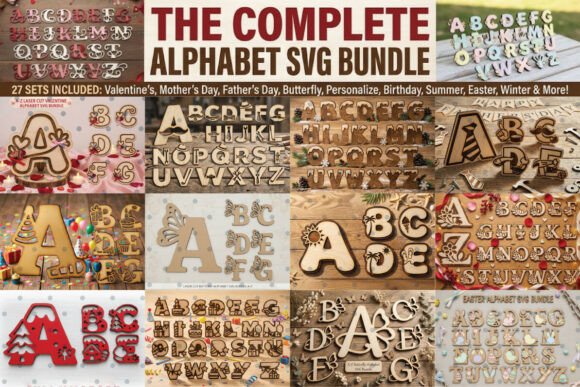
The Complete Alphabet SVG Bundle
Ulasan Lengkap: The Complete Alphabet SVG Bundle – Solusi Final untuk Desain Kreatif Anda
Ingin memperluas katalog produk kerajinan, membuat hadiah pribadi, atau hanya menambah sentuhan kreatif pada dekorasi rumah? The Complete Alphabet SVG Bundle adalah paket lengkap yang dirancang khusus untuk pemotong laser, mesin CNC, dan pemotong vinil. Dengan 27 set alfabet unik bertema, Anda tidak akan pernah menghadapi keterbatasan dalam menciptakan karya yang memukau.
Kenapa Anda Harus Memilih Paket Ini?
- Beragam Tema: Dari Valentine’s Day dengan motif hati, Mother’s Day penuh bunga, hingga Father’s Day dengan peralatan dan tali.
- Fleksibilitas Desain: Set alfabet lengkap A‑Z memungkinkan Anda membuat nama custom, papan nama, dan banyak lagi.
Set Tema Terpopuler
- Valentine’s Day – Alfabet berdesain hati romantis.
- Mother’s Day – Floral elegan untuk merayakan ibu.
- Father’s Day – Desain tool & tie, nuansa maskulin.
- Nature & Animals – Motif kupu-kupu, bunga, dan hewan.
- Celebrations – Alfabet pesta ulang tahun dan perayaan.
- Seasonal – Tema musim panas (palm tree), musim dingin (salju), dan Paskah (kelinci, telur).
- Personalized – Desain bersih dan serbaguna untuk nama atau signage.